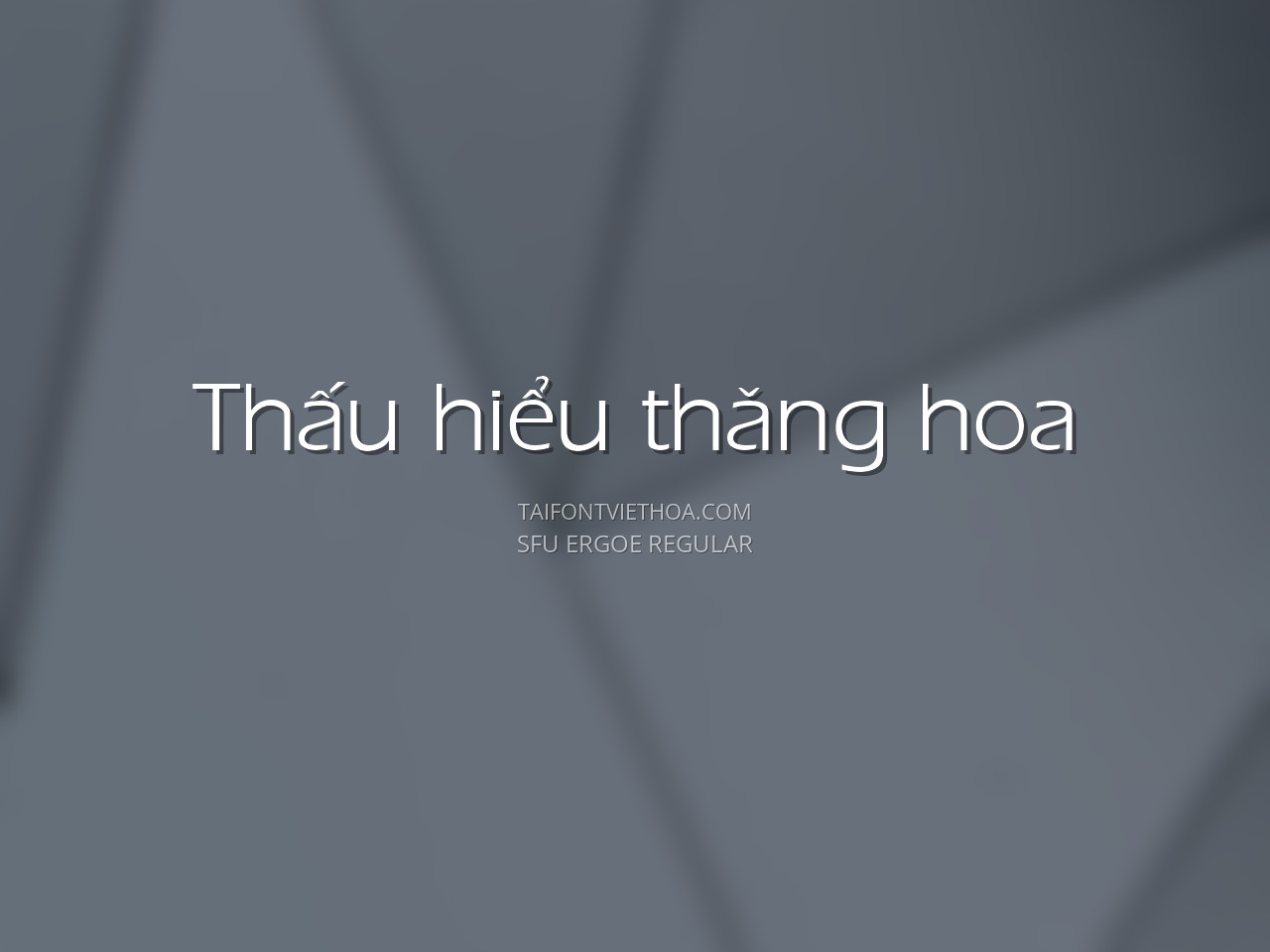
Font việt hóa SFU Ergoe
Giới thiệu về font SFU Ergoe – Kiểu chữ sans-serif hiện đại theo phong cách ergonomic
SFU Ergoe là phiên bản Việt hóa của font Ergoe – một kiểu chữ sans-serif được phát triển với triết lý thiết kế ergonomic (công thái học), mang đến sự thoải mái, dễ đọc và thân thiện với người dùng. Font được xây dựng trên cấu trúc hình học mềm mại, kết hợp với sự cân bằng giữa tính hiện đại và cảm giác tự nhiên, rất phù hợp với các thiết kế UX/UI và nội dung số.
Phiên bản SFU Ergoe đã được Việt hóa đầy đủ, hỗ trợ dấu tiếng Việt cùng hơn 90 ngôn ngữ khác. Taifontviethoa.comđã sưu tầm, chọn lọc và chia sẻ bộ font này nhằm đáp ứng nhu cầu thiết kế thực tiễn trong thời đại kỹ thuật số, đặc biệt là với các sản phẩm số yêu cầu trải nghiệm người dùng mượt mà và dễ tiếp cận.
Thiết kế thân thiện – dễ đọc và ứng dụng tối ưu trong môi trường số
SFU Ergoe có hình dáng sans-serif hiện đại với các đường nét bo tròn nhẹ ở đầu chữ, mang lại sự mềm mại, thoải mái và dễ chịu cho mắt người đọc. Font được tối ưu hóa về khoảng cách chữ, độ cao chữ và độ rộng để đảm bảo khả năng hiển thị rõ nét trong mọi tình huống – từ văn bản dài đến các giao diện điều hướng.
Ứng dụng lý tưởng: thiết kế giao diện người dùng (UI/UX), website, ứng dụng mobile, tài liệu hướng dẫn, bản trình bày, slide doanh nghiệp và bảng dữ liệu. Ngành nghề phù hợp: công nghệ số, giáo dục trực tuyến, phần mềm, y tế số, startup, thương mại điện tử và các thương hiệu hướng đến sự thân thiện, tiện ích và chuyên nghiệp.